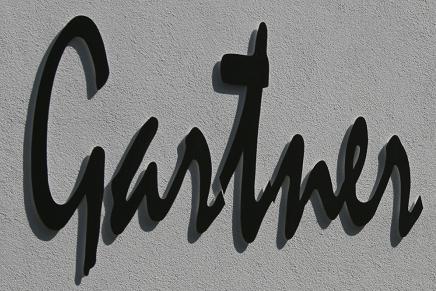
Kann mir jemand sagen, um welche Schriftart es sich hier handelt?
(Bitte nicht iritieren, das ist an einer Hauswand, daher der Schatten)
Ich denke mal, das ist eine Blechschrift an einer Hauswand. Und aus 'nem arg schrägen Winkel fotografiert. Und an den Anschlüssen (r-t-n) ist das Blech ein wenig verbeult ...
Alles andere wäre echt mehr als nur grob fahrlässig :lol:
nun, erstmal danke für die Auskunft. Das Bild ist Frontal gemacht, nicht schräg, wobei es wirklich eine Blechschrift an der Hauswand ist... :wink:
Generell stelle ich mir die Frage, ob sich der Charakter der Mistral mit dem Anbringen als relativ große Metalllettern auf Verputz verträgt.
Warum nicht? Die relativ starke Strichstärke »trägt« doch recht gut – aber natürlich nur, wenn die Buchstaben auch wirklich VERBUNDEN sind. Das muss doch sogar der Laie sehen. :evil:
Ich habe den Schriftzug zuhause nachgebaut (nur auf dem Rechner). Zwischen den Kleinbuchstaben sind minimale Abstände zu erkennen, wo die Buchstaben eigentlich aneinander stoßen sollen; also auch wie auf dem Bild aber doch sehr viel weniger schlimm.
Wenn der Beschriftungsspezialist nun eine billige Version der Mistral als Vorlage genommen hat, wird er wohl die schlecht zugerichtete Schrift 1:1 auf die Metallbuchstaben übertragen haben…
Oder derjenige der die Buchstaben angebracht hat hat sich „verbohrt“ und wollte die Schraubenlöcher nicht neu ansetzen…
Irgendetwas stellt sich bei mir quer, wenn ich handschriftliche Schriften in so einer (Über)produzierung sehe.
An die Wand gepinselt: ja!
Auf Papier geschrieben (und sei es als digitaler Font im Laserdruck): ja.
Aber aus Alu geschnitten, lackiert, und mit 3cm Abstand an die Wand geschraubt: da verliert sich für mich der handschriftlich-spontane Moment den die Schrift eigentlich hat. Zu dieser Produktionsmethode passt eher eine wohldurchdachte Serifenlose (und umgekehrt).
Klar: Schreibt es das Firmen-Erscheinungsbild vor, muss eine Lösung gefunden werden. Ich würde in diesem Fall zumindest den Abstand zur Wand vermeiden und dem ganzen so den Schild-Charakter etwas nehmen. Und: Die Buchstabenabstände... das müsste anders werden :)
Gibt es eigentlich noch Schildermacher, die auch grafische Qualitäten haben?
Meine Erfahrungen mit dieser Berufsgruppe (viel schlimmer noch als bei Druckereien, leider): Die haben eine tolle Druckmaschine, Schneidplotter, etc. gekauft, und sind Maschinenbediener geworden. Allenfalls jammern sie noch, wenn ein Kunde eine technisch schlechte Vorlage mitbringt, die sich so am Gerät nicht umsetzen lässt. Und übergibt der Kunde ihnen den Auftrag samt Gestaltung ganz ("macht mir ein Schild mit folgendem Text: ...") kommt zielsicher Unterirdisches heraus...
Schildermaler waren doch früher™ Gestalter zwischen Typografie und Architektur, und zumindest einige hatten auch gestalterisch einen qualitativ Anspruch.
98 % meiner erfahrungen sind genau so.
schildermacher sind einfach handwerker. die nehmen lineal und bleistift
anstatt auge und köpfchen. ;) aber es gibt auch gute ... man muss sie nur
finden. ich habe aber auch schon alles mögliche erlebt.
das stimmt, ist aber kein grund zur schlechten arbeit, wenn die fliesenleger oder schreiner so arbeiten würden, dann hätten sie nicht lange überlebt.
ich kann es oft auch nicht verstehen, was da in der branche so abgeht?
die ausführung eines fliesenlegers oder schreiners muss ja auch nicht zuerst am computer gemacht werden. das sind typische handwerksberufe die man meistens 3 jahre gelernt hat.
schildermacher wird eher selten als lehrberuf genommen und darum haben die macher selbst kaum ahnung mit dem computer umzugehen, bzw. einen sinn für design, schrift und typografie. viele stammen aus ganz anderen brachen von maler über lackierer, reprografen, schaugewerbehersteller bis hin zu ehemaligen plakatmalern und messebau ist da wirklich alles dabei. diese machen einen computerkurs an der vhs, lernen windows und corel und kaufen sich einen plotter. generell ist das (wie auch mediengestalter) ein beruf den das arbeitsamt gerne empfiehlt wenn man schonmal mit word gearbeitet hat, darum gibts gerade in der branche viele seiteneinsteiger.
die meisten haben ahnung von materialen, möglichkeiten der anbringung, lichtinstallation und so weiter. aber wenige haben ahnung von typografie und design. was ja eigentlich auch nicht deren aufgabe ist – nimmt man es genau. nur viele plotterfreunde stellen halt auch gern logos her, weil sie ja alles dazu vorhanden ist – bis auf die ausbildung dafür. viele überschätzen einfach ihre leistungen. ich habe z. b. auch 2 linke hände und bekomm noch nicht mal einen nagel gerade in die wand. also suche ich mir jemanden der es kann – fertig aus. so sollten es die plotterleute auch machen. sie sollten sich auf ihre handwerklichen fähigkeiten berufen und uns die gestaltung überlassen, dann sucht man sich noch 'nen dritten der auch aufpasst das alles richtig an die wand kommt (also so wie der gestalter sich das überlegt hat, richtige buchstaben abstände etc.) und alle sind zufrieden. ich plane ja auch keine häuser nur weil ich 'ne cad-software auf dem rechner habe.